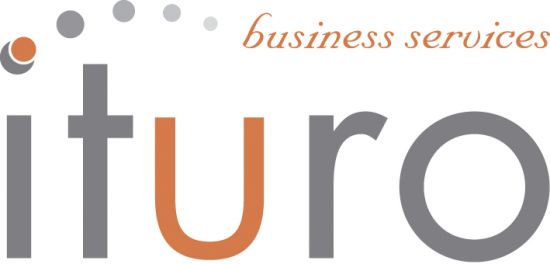
Hier ein Logo: Sagt mir wer welche Schrift das ist?
Ist das überhaupt als Schrift gesetzt? ich finde nichts passendes. Avantgarde kommt noch am nähestens dran, aber das U stimmt nicht.
Futura ist zu dünn, hab ich auch schon probiert. Aber mit Century Gothic hab ich das u hinbekommen. Danke für den Tipp.
Und nächste unverschämte Frage: Die Schrift darüber, "business services"?
was für futura schnitte hast du? es ist die FUTURA BOOK
Haaaa, super! Hab ich natürlich beides nicht. Hab nur Futura Condensed und Medium, nicht Book. Und die Nuptial hab' ich auch nicht. Aber der Schriftzug muss eh ersetzt werden, dann nehme ich eine andere Calligrafic, der neue Schriftzug ist ja auch länger und Stauchen will ich auf keinen Fall.